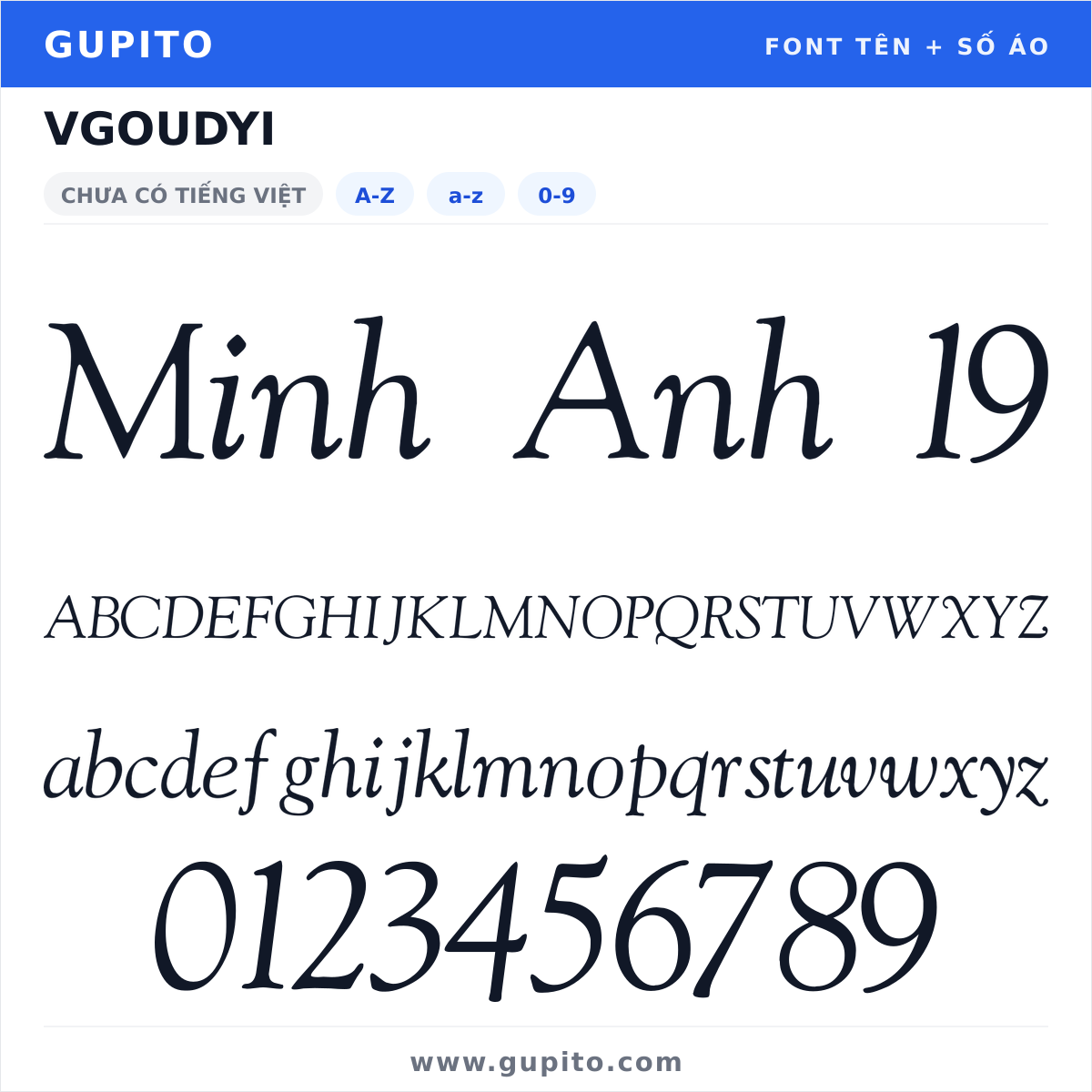
VNI-Goudy-Italic
VNI-Goudy-Italic · Font VGOUDYI in tên áo bóng đá, áo lớp, số áo · chữ nghiêng thanh lịch
Font VGOUDYI với nét chữ nghiêng thanh lịch, có đủ bảng chữ cái và số, lý tưởng để in tên áo bóng đá, áo lớp, áo nhóm, quà tặng. Bộ chữ VNI-Goudy-Italic dùng để in chuyển nhiệt lên áo đấu, áo lớp, áo nhóm và đồ thể thao theo yêu cầu. Kiểu dáng: chữ nghiêng thanh lịch. Font dùng cho chữ không dấu và số áo. Có đủ bộ chữ số để in số áo. Từ khoá liên quan: font vgoudyi, font in ten ao, font in so ao, font ao bong da, font ao lop, font chu nghieng, font co bang so, font in chuyen nhiet.